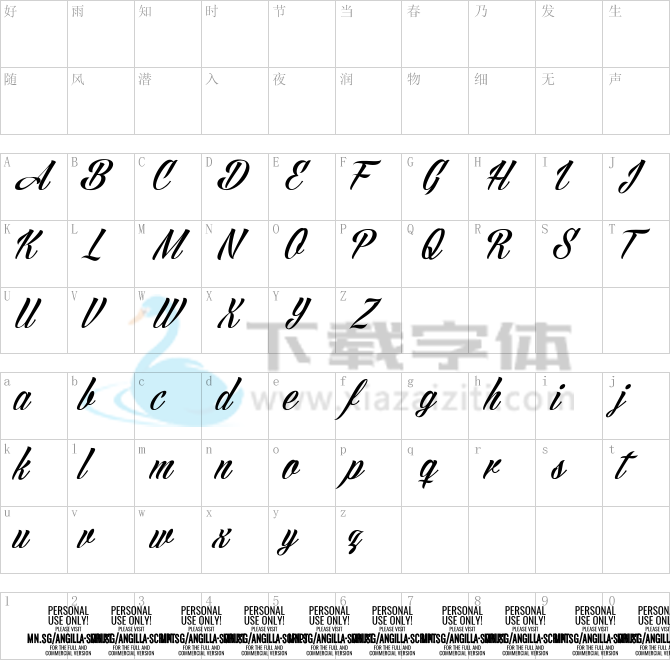
Angilla Script PERSONAL USE.ttf字体下载,这款字体结构工整、笔画清晰,兼顾美观与易读性,适用于标题、正文、海报、包装、LOGO 等多种场景。字形优雅稳定,风格百搭耐看,适配日常排版与创意设计,让文字呈现更舒适、更具质感。Angilla Script PERSONAL USE.ttf字体下载一笔一画,皆是细节,以均衡的比例、流畅的线条打造舒适视觉体验,字形端正大气,风格简约现代。无论是商业设计、品牌宣传还是日常排版,都能轻松驾驭,让文字更有格调与力量。Angilla Script PERSONAL USE.ttf字体下载字体下载。
• 字体名称:Angilla Script PERSONAL USE